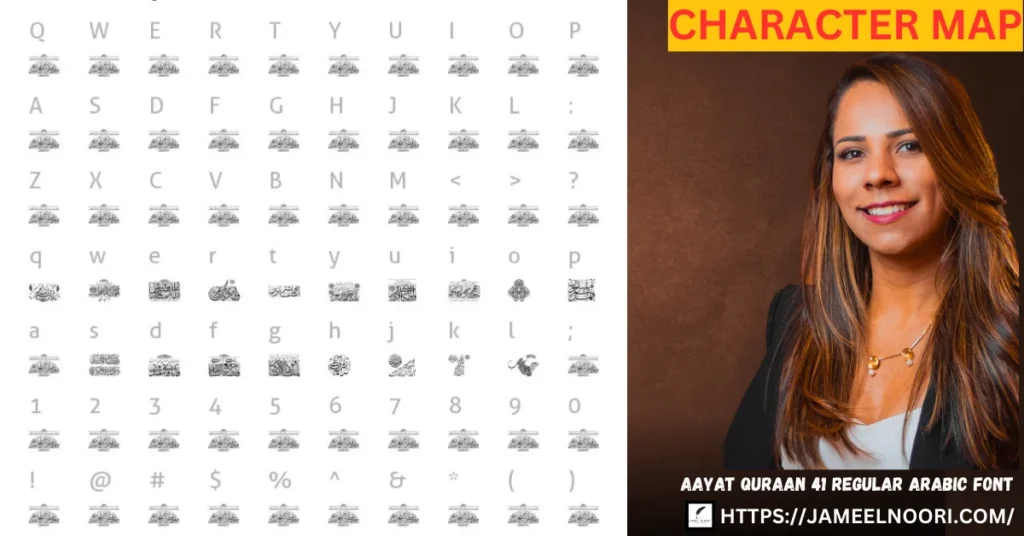
Aayat Quraan 41 Regular Arabic Font – Stylish TrueType Font
Aayat Quraan 41 Regular Arabic Font ek Regular TrueType Font hai jo Pakistan me users ke liye specially design kiya gaya hai. Is font ko ab tak 13,962 times download kiya ja chuka hai aur 365 users ne is font ko 4.53 out of 5 rating di hai. Is font ke zariye aap Urdu aur Arabic content ko easily design kar sakte hain aur apni digital projects me ek professional touch de sakte hain. Is article me hum apko is font ke bare me complete information dy gy taki aap bina time waste kiye is font ka best use kar saken.
Features of Aayat Quraan 41 Regular Arabic Font
Aayat Quraan 41 Regular Arabic Font me kuch unique features hain jo isay market me alag banate hain:
FeatureDescription
Font TypeTrueType Regular
Language SupportArabic & Urdu
Character MapComplete calligraphy support
Key Advantages:
• Smooth ligatures for professional designs
• Perfect for web, print, and social media
Aayat Quraan 41 Regular Arabic Font character map and calligraphy example
Explore the character map of Aayat Quraan 41 Regular Arabic Font for seamless Urdu and Arabic text design.
Why Choose Aayat Quraan 41 Regular Arabic Font?
Aayat Quraan 41 Regular Font ko choose karne ke bohot se reasons hain. Pehla reason iska high readability hai jo Urdu aur Arabic content me perfect fit hai. Dusra reason iska traditional calligraphy style hai jo Quraan aur Islamic projects ke liye ideal hai. Ye font Lahore, Karachi aur Pakistan ke dusre cities me bhi bohot popular hai.
• Elegant Arabic design
• Easy to read in digital and print format
Compatibility and Usage in Pakistan
Aayat Quraan 41 Regular Arabic Font Pakistan me har tarah ke design projects ke liye suitable hai:
• Digital media: Social media posts, websites
• Print media: Brochures, flyers, books
• Islamic content: Quranic verses, Islamic calligraphy
Ye font Lahore, Karachi aur Pakistan ke har city me designers ke liye top choice hai.
What is Aayat Quraan 41 Regular Arabic Font?
It is a TrueType font designed for Urdu and Arabic content, highly readable and perfect for digital and print use.
Can I use it for Quranic verses?
Yes, it is ideal for Islamic content including Quranic calligraphy.
Does it include full Arabic character support?
Yes, the character map includes full Arabic ligatures and special symbols.